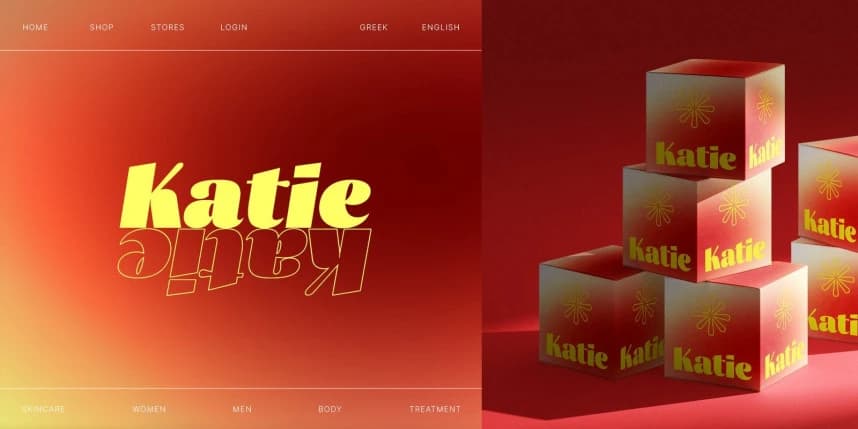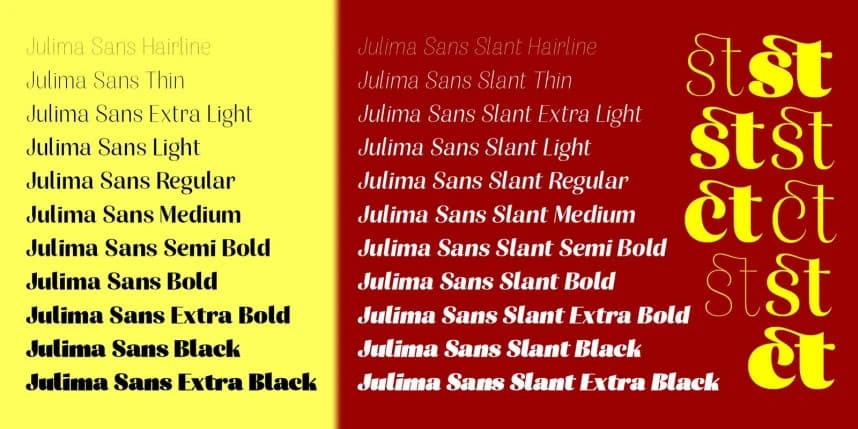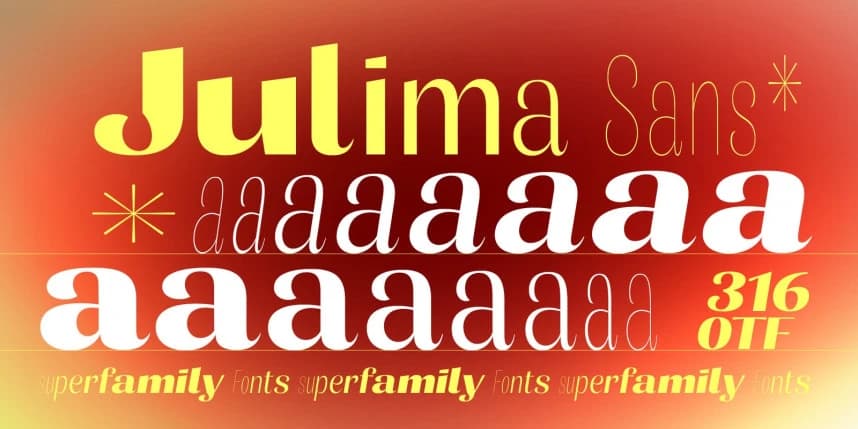
Julima Yazı Tipi
Julima Font, güçlü görsel etkiyi olağanüstü esneklikle sunmak üzere tasarlanmış çağdaş bir gösteri sans serif süperfamilyasıdır. İnsani bir temele dayanan bu font, temiz geometriyi ince organik dokunuşlarla dengeler ve bu sayede kalın başlıklar için de uygundur.
Julima Font, çarpıcı görsel etkiyi olağanüstü esneklikle sunmak üzere tasarlanmış çağdaş bir ekran tipi sans serif süperfamilyasıdır. İnsancıl bir temele dayalı olarak, temiz geometriyi ince organik dokunuşlarla dengeler ve bu da onu hem cesur başlıklar için uygun hale getirir.